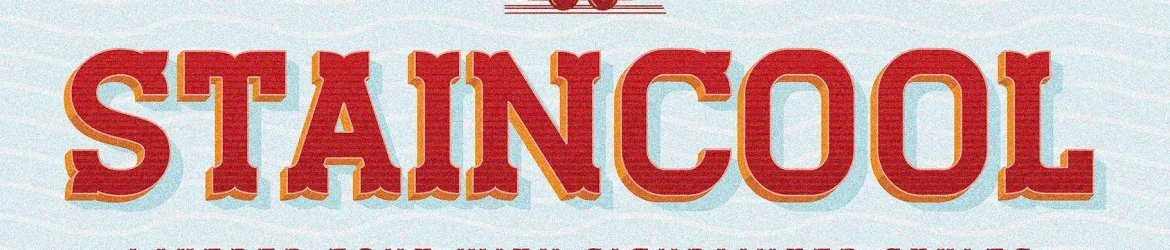
Staincool Layered Font – Download Grátis
Esta fonte é ideal para aqueles que querem adicionar um toque único a seus projetos visuais. Inspirada no estilo artístico dos pintores de sinais, apresenta uma textura única e vibrante, perfeita para criar elementos gráficos dinâmicos e memoráveis. A Staincool Layered Font é um conjunto composto por seis camadas fáceis de usar, que permitem uma grande flexibilidade. Inspirada no artista do sinal, a fonte apresenta um estilo retro interessante. Ela nasceu da combinação entre o famoso tipoface Stengkol 04 e as novas tecnologias 3D. Ideal para criações em etiquetas, produtos personalizados, embalagens, logotipos ou símbolos, a Staincool Layered Font oferece uma escolha versátil de formas que vai encantar o olhar do seu público-alvo. Ela é perfeita para quem busca estilizar seus projetos com um toque retro e criativo, trazendo um brilho único aos designs.